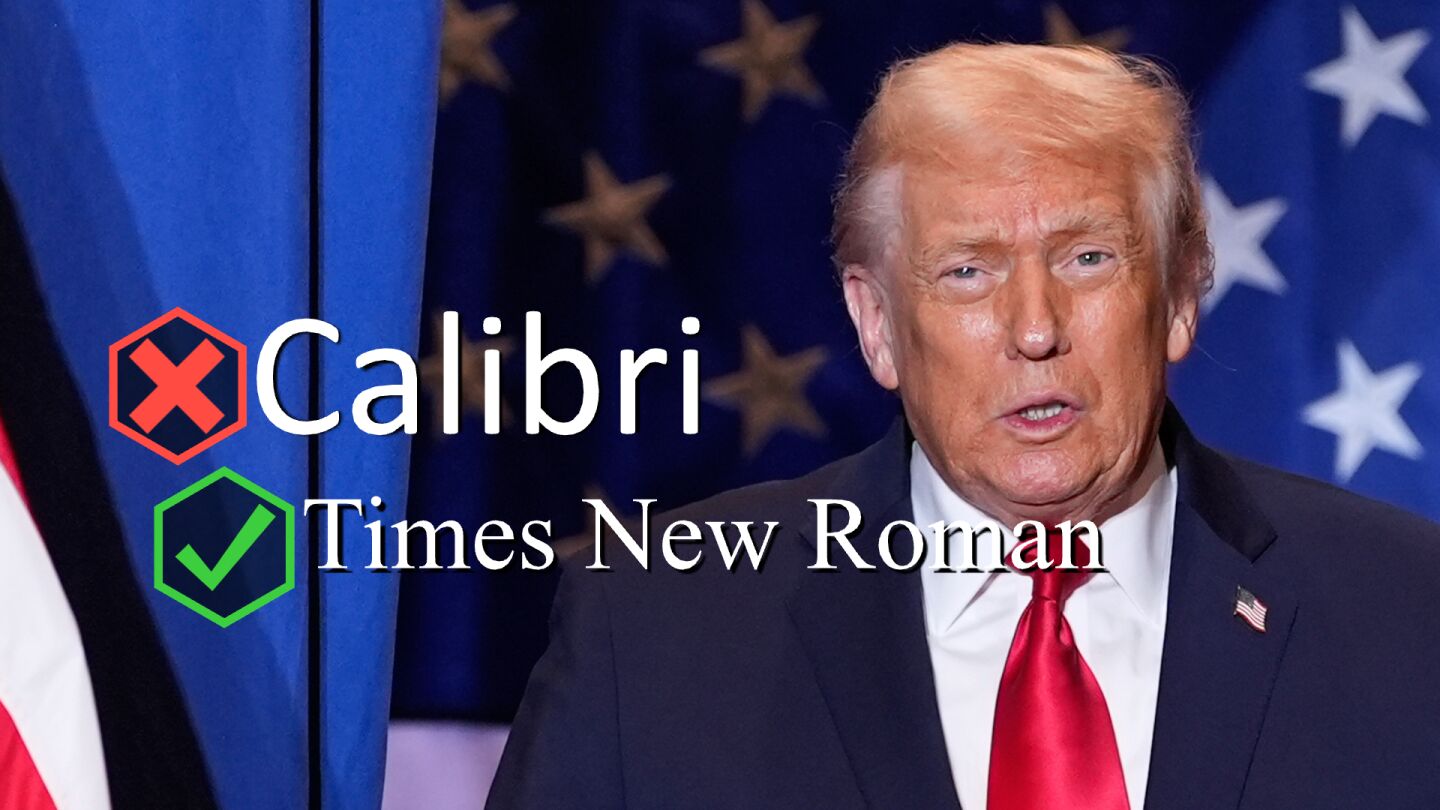
EEUU declara la guerra a la tipografía Calibri por considerarla 'woke' y ordena volver a la Times New Roman
El contexto Esta medida revierte la decisión del Gobierno de Biden sobre el uso de Calibri en los documentos oficiales de los departamentos en 2023, que buscaba hacer que las páginas web y publicaciones fueran más accesibles. Rubio esgrime ahora que la Times New Roman restablece el decoro y la profesionalidad.
El Departamento de Estados Unidos ha ordenado dejar de utilizar la tipografía Calibri y sustituirla por la Times New Roman en una disputa ideológica que llega así al tipo de letra en los documentos oficiales.
El secretario de Estado de EEUU, Marco Rubio, considera que que Calibri, sin adornos en los trazos, simboliza la cultura 'woke'. Mientras, la Times New Roman, según ha dicho, restablece el decoro y la profesionalidad.
Esta medida revierte la decisión del Gobierno de Biden sobre el uso de Calibri en los documentos oficiales de los departamentos en 2023, que buscaba hacer que las páginas web y publicaciones fueran más accesibles.
El entonces secretario de Estado, Antony Blinken, implementó el cambio por recomendación de grupos internos de diversidad y discapacidad, según informó entonces la 'CNN', al considerar Calibri más accesible para personas con dislexia y discapacidad visual, por sus letras de ángulos más redondeados, sin trazos decorativos en los extremos y mayor espacio entre caracteres.
Según los principales medios estadounidenses, Rubio ha afirmado en una nota interna al personal que el cambio a la tipografía Calibri ordenada por Biden es un ejemplo de políticas "ineficientes" en favor de la diversidad. "Regreso a la tradición: se exige Times New Roman en tamaño 14 para todos los documentos del Departamento", reza el asunto del memorando citado por los medios locales.
"La tipografía moldea cómo se perciben los documentos oficiales en términos de cohesión, profesionalidad y formalidad" y el regreso a la letra Times New Roman busca "restaurar el decoro y la profesionalidad en los trabajos escritos del Departamento", afirma Rubio en el documento.
"Esta norma de formato está en consonancia con la directiva del presidente Una sola voz para las relaciones exteriores de Estados Unidos, que subraya la responsabilidad del departamento de presentar una voz unificada y profesional en todas las comunicaciones", añade el mensaje.